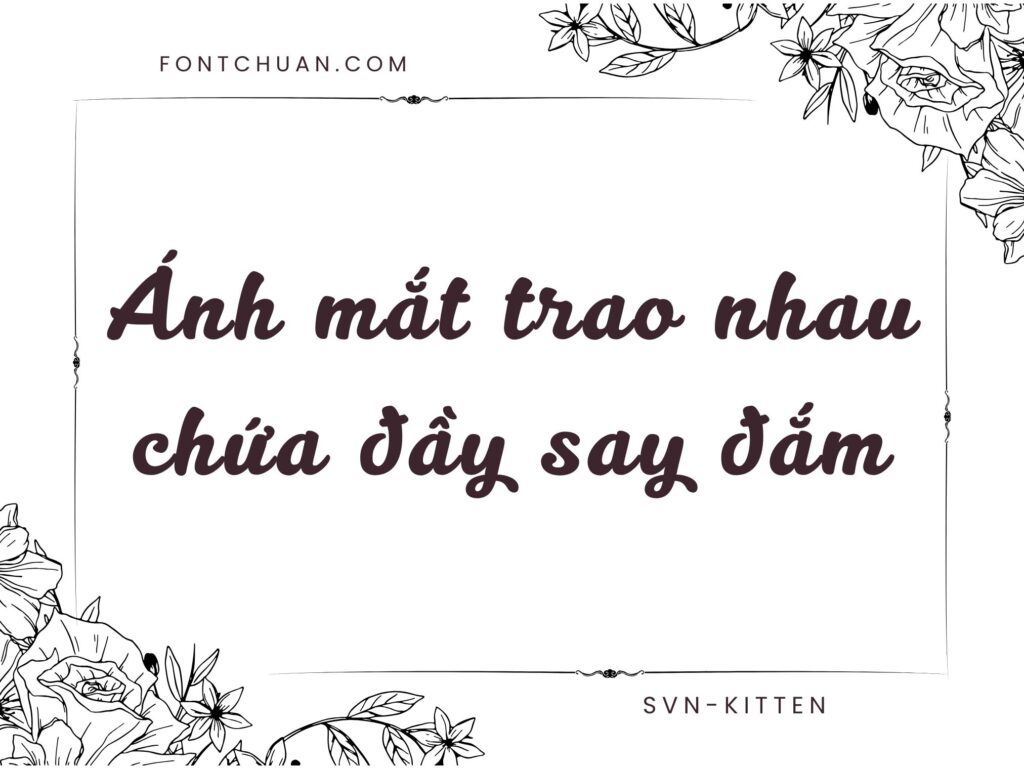
Font SVN Kitten Việt Hóa
Tác giả Font: Cosimo Lorenzo Pancini, Isabella Ahmadzadeh
Font SVN Kitten là phiên bản Việt hóa của kiểu chữ Kitten, được thực hiện bởi STYLEno.1 Fonts. Kitten là một họ font script đa trọng lượng với phong cách vẽ biển hiệu, được thiết kế bởi Cosimo Lorenzo Pancini và các biểu tượng mèo được thiết kế bởi Isabella Ahmadzadeh. Với đặc trưng mang hơi hướng Font chữ viết tay, font này sở hữu các nét cong mềm mại và đậm nét ở trọng lượng thông thường, lý tưởng cho thiết kế logo và sử dụng trong tiêu đề, trong khi các trọng lượng nhẹ hơn, cũng như biến thể Monoline và Slant cô đọng, phù hợp cho các đoạn văn bản dài. Kitten hỗ trợ hơn 40 ngôn ngữ sử dụng bảng chữ cái Latin, với đầy đủ các dấu và ký tự đặc biệt. Font này bao gồm năm trọng lượng và ba biến thể phong cách: Regular, Slant và Swash. Kitten tận dụng tối đa các ligature OpenType để tránh va chạm chữ cái ở chữ hoa và cung cấp các ký tự thay thế cùng một loạt các ligature cho vẻ ngoài thủ công, tự nhiên hơn. Các swash có thể được truy cập thông qua bảng glyph hoặc bằng cách gõ từ một đến sáu dấu gạch dưới sau chữ cái. Một khoảng trắng theo sau bởi từ một đến tám dấu gạch dưới sẽ tạo ra các hình bóng mèo khác nhau.
SVN Kitten phù hợp cho các thiết kế như logo thương hiệu, tiêu đề, bao bì sản phẩm và các ấn phẩm truyền thông. Các ngành nghề như quảng cáo, giáo dục và ẩm thực có thể tận dụng font này để tạo điểm nhấn trong thiết kế. Ngoài ra, font cũng thích hợp cho các sự kiện như Tết, Giáng sinh, Valentine và các lễ hội khác.